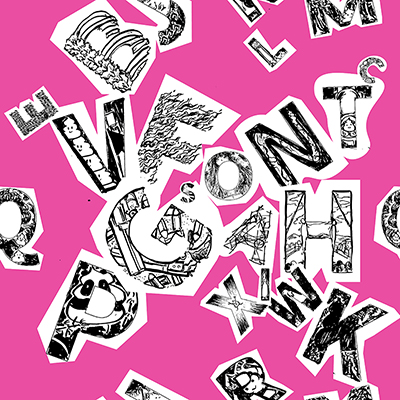
ゆるすげえ
スタイリッシュなアルファベット柄
今までの並べ方とは違うようにしたいと思います。结局,意外にも多くの色とマッチしているので、私はこの作品の背景に他のいくつかの異なる色を用意しました。(許 靖易)(許 靖易)
元々フォント用に制作をされていましたが、パターンとして採用されました。一つ一つのアルファベットを見ていただくと、アーティストの方の遊び心が垣間見ることができます。(TEN TONE)(TENTONE)